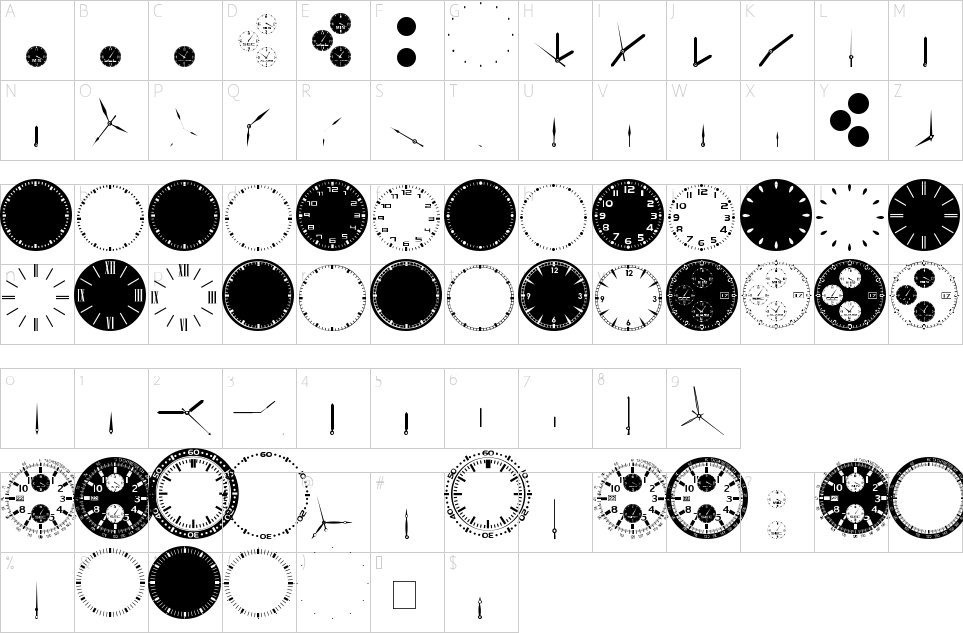
GA Clock Dial Round Font
A fonte GA Clock Dial Round é uma elegante escolha para qualquer projeto que valorize detalhes meticulosamente criados, como relógios modernos ou designs gráficos contemporâneos. Desenhada por Gurgen Alaverdian e disponível gratuitamente tanto para Windows quanto para Mac, esta fonte adiciona um toque sofisticado e único aos seus projetos digitais. Com suas linhas arredondadas perfeitas e detalhes cuidadosamente definidos, GA Clock Dial Round oferece uma experiência visual única que é tanto funcional quanto estética, tornando-a uma opção ideal para designers gráficos em todo o Brasil. A fonte foi baixada 25.801 vezes, demonstrando seu valor e aprimoramento por usuários atentos à qualidade de design. Seja para projetos profissionais ou pessoais, a GA Clock Dial Round é uma excelente adição que eleva qualquer projeto gráfico digital ao próximo nível.
Mapa de caracteres da fonte GA Clock Dial Round Font